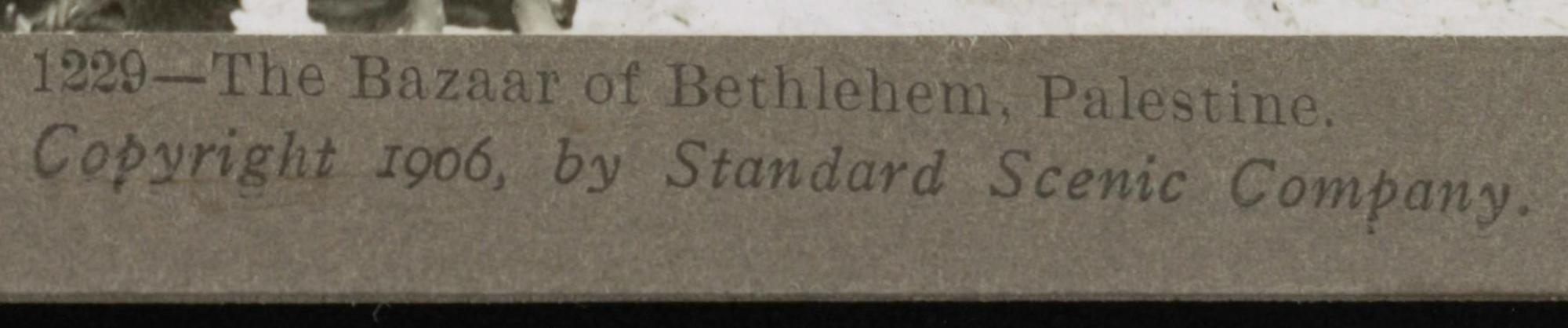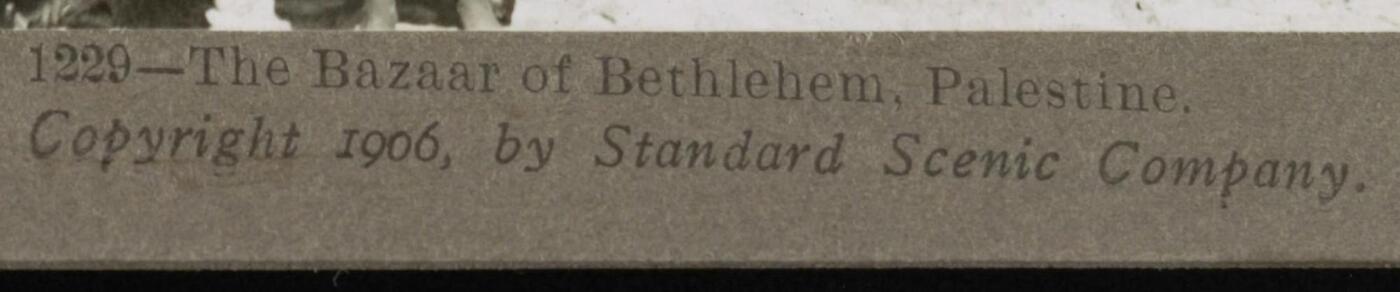
Gesperrte Kursive von 1906 (Standard Scenic Company) – Fotolegende »The Bazaar of Bethlehem, Palestine«
auf einem der Fotos der Serie Photographs of Life in Palestine (ca. 1896–1919) (»1229—The Bazaar of Bethlehem, Palestine«) wird eine gesperrte und dadurch fast dicktengleich wirkende Kursive für den 1906er-Copyrightvermerk in der Bildlegende eingesetzt.
Um welche Schrift handelt es sich? Alternativen habe ich genug, es geht mir um genau die verwendete Schrift (sie braucht nicht in digitalisierter Form zu existieren).
Falls ihr auch die darüber stehende Aufrechte identifizieren könnt, benennt diese gerne ebenfalls.
Die Kursive ist vermutlich die Old Style Antique Italic, von Miller & Richard. Manchmal vermarktet unter den Namen OS Antique 7. Oder eine spätere Schrift, die von einer anderen Schriftgießerei bzw. von einen Schriftsetz- und Gießmaschinenhersteller angeboten wurde.
Der exakte Name der geradestehenden Schrift herauszufinden, ist m.W.n. unmöglich.
Bis ins frühen 20. Jahrhundert war es üblich, dass Schriftgießereien Schriften untereinander austauschten und auch von einander geklaut haben. Bei so – mit Verlaub – generischen Schriften ist es oft nicht möglich, den Ursprungsanbieter herauszufinden, geschweige die tatsächliche Firma, die die jeweilige Druckerei beliefert hatte. Auch bei der Kursive, die schon etwas eigenartiger ist, würde ich nicht darauf wetten wollen, dass die Druckerei unbedingt Kunde von Miller & Richard war. Später war es tatsächlich so, das bestimmte Schriften nur von einer bestimmten Firma erhältlich waren. 1906 war das noch sehr selten.
Die O.S. Antique Italic läuft breiter, hat besser proportionierte Versalien und selbstbewusstere Serifen in den Minuskeln. Doch vom Gesamtduktus her ist sie tatsächlich eine heiße Spur.
Mich reizt in der an sich bewegten Schrift meiner Vorlage dieser merkwürdige Anflug von Charakterlosigkeit und Anonymität (“nondescript”). Die verlinkte O.S. Antique Italic wirkt im Vergleich wie eine voll ausgearbeitete Displayschrift.
Du meinst, es gab dann einfach diverse Nachahmer der O.S. Antique Italic und die Schrift aus meiner Vorlage ist einer davon?
Um 1906 gab nur eine begrenzte Auswahl an ähnlichen Schriften. Unter Umständen hatte Monotype oder Linotype schon eine ähnliche Schrift gehabt. Entscheidend ist, wo der Druck gedruckt wurde. Und ie OS Antique Italic wurde ich nicht ganz ausschließen. Die Schrift ist von den 1850er und wurde per hand geschnitten. Pantographen für den Bleisatz-Herstellung hab’ es noch nicht. Die Schriftbilder zu diesem Zeitpunk waren etwas unterschiedlich von Größe zu Größe. Ich habe es selbst nicht genau nachgeschaut.
Das ist ein guter Hinweis. Die Ähnlichkeit wird stärker, wenn man in der Schriftprobe an die kleinen Größen (8 Pt.) heranzoomt, wobei die Bildauflösung zugegeben recht grob dafür ist. Der Vergleich scheint dann sogar teilweise den Verlust von Gewicht und Detail in den Versalien herzugeben, der kennzeichnend für die Vorlage ist.